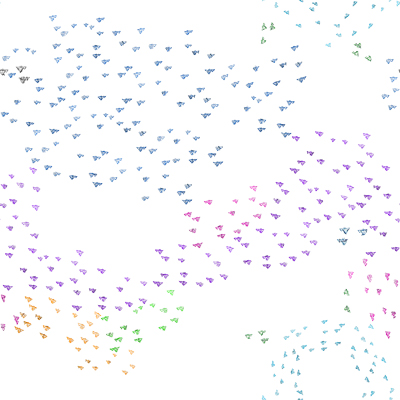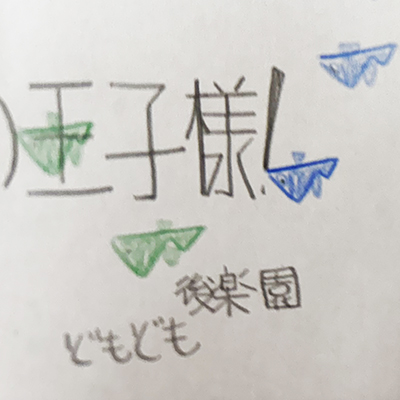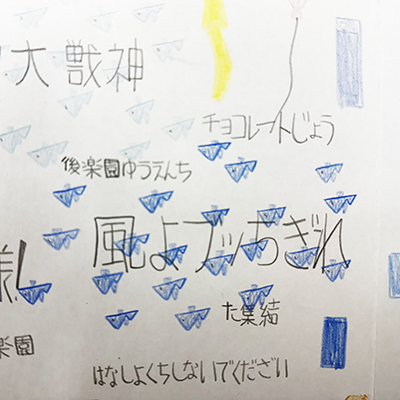
魚群探知機
魚の群れって、こんな感じ
色鉛筆で何枚にも描かれた小さな魚を無数に集めると、海の中の風景のようになりました。(山盛幸一)
優功さんは双子で(兄は弘光さん)、お二人とも自閉症です。優功さんの作品の特徴は、好きなドラマやアニメのタイトルと一緒に好きな食べ物や風景、物を画用紙にめいいっぱい描くのが特徴です。(アトリエライプハウス)